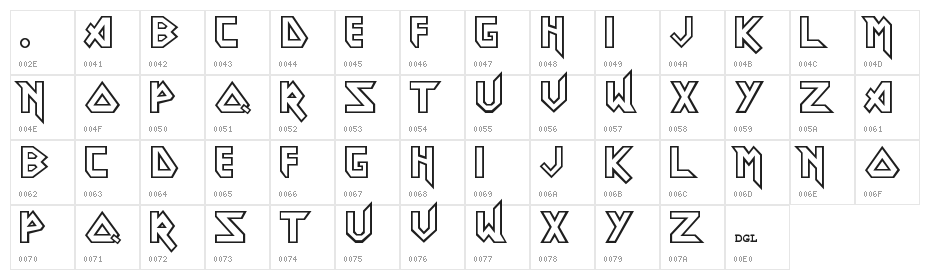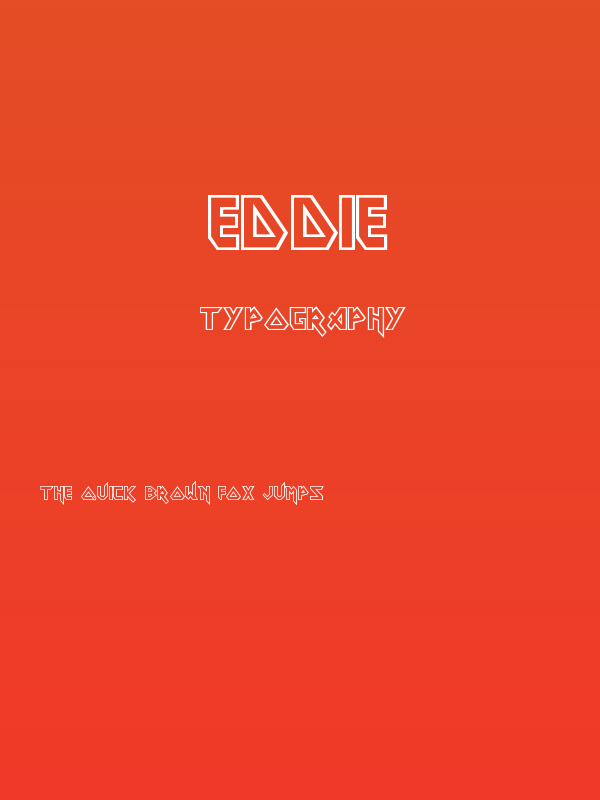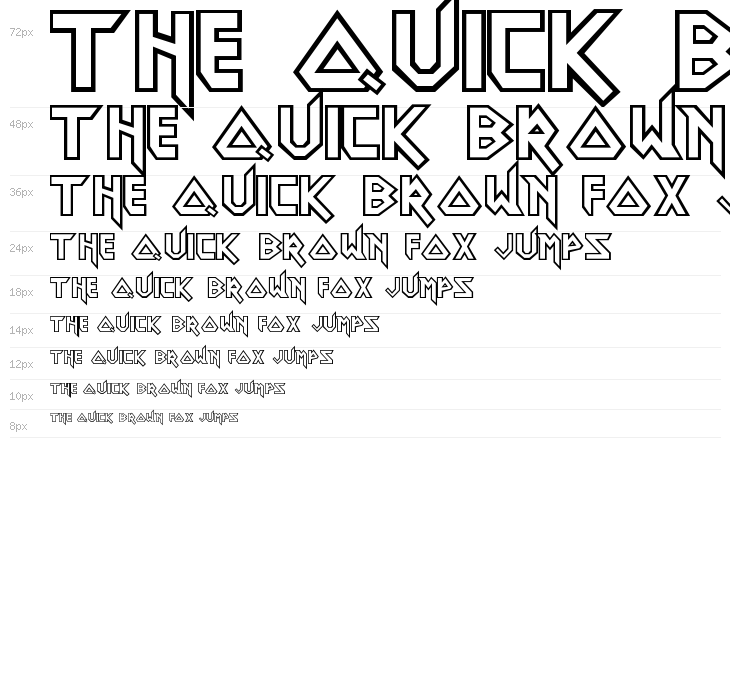
Eddie Font
| Estilo general | Futuristic, Industrial |
| Caso de uso | Logos, Headlines, Posters |
| Proyectos propuestos | Ideal for video game graphics, music album covers, posters, and branding that requires a bold, edgy look. |